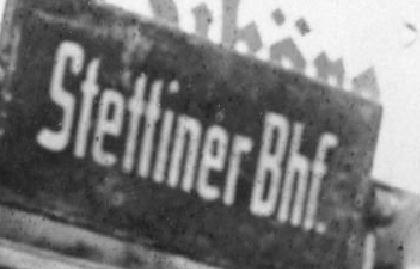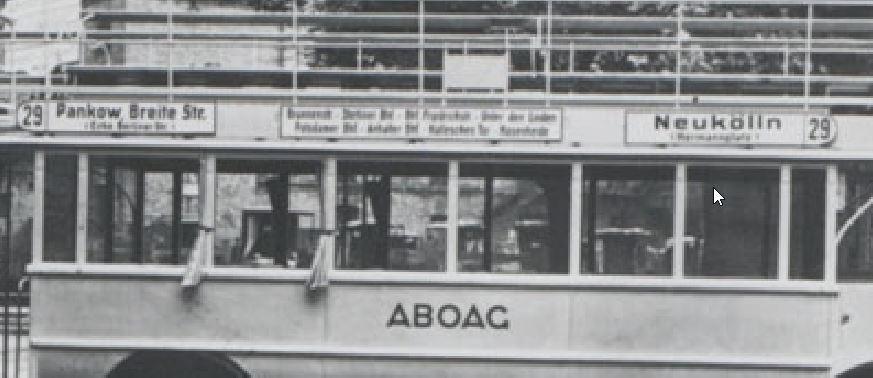
Suche Schrift an Fahrzeugen der ABOAG/BVG (Berliner Verkehr) aus der Vorkriegszeit.
die Berliner Verkehrsbetriebe (bis 1929 ABOAG, danach BVG), verwendeten für ihre Streckenanzeige an ihren Fahrzeugen ein Schriftbild, welches ich bisher noch nicht ermitteln konnte.
Anbei sind einige Abbildungen von Streckenschildern (Netzfunde/Buchkopien). Vielleicht könnt ihr mir dazu weiterhelfen.
Ich vermute, dass es eine Schrift ist, die ähnlich bei der Länder- oder Reichsbahn, speziell für das Unternehmen erstellt wurde und darüber hinaus nicht weiter im Gebrauch war.
Es würde mir auch helfen, eine sehr ähnliche Schrift zu finden. Die der Schrift vorkommenden (aus meiner Sicht) Besonderheiten wie die Gestaltung des große "S" oder kleinen "g" würde ich dann anpassen. Anpassen für Schilder, die ich im Modellbau verwenden will.
Solche Schilder waren entweder von Schildermalern handgemalt oder es gab einen nur intern verwendeten Buchstabensatz, der keinen Namen brauchte, weil er nicht gehandelt wurde. Man wird das also mit großer Wahrscheinlichkeit nicht benennen können.
Ausnahme: Neukölln und Wilmersdorf könnten auf der DIN 1451 beruhen.
Wobei der, zumindest firmenintern, standardisiert war. Denn alle Fahrzeuge, Busse und Straßenbahnen, hatten über Jahrzehnte diese Schrift im Einsatz.
Ich werde mir mal Plakative Grotesk, Schilder Grotesk und Sturkopf Grotesk näher anschauen und Buchstaben entsprechend ändern. Beispiel das kleine "a", welches ja so eine Art Hängebauch hat.
Hatte schon Kontakt aufgenommen. War auch im BVG Archiv und habe diverse digitale Bibliotheken geflöht. Hat alles keinen Erfolg gebracht.
Das liegt wahrscheinlich daran, dass das BVG Archiv 1943 durch einen Bombenangriff fast komplett zerstört wurde. Es liegen somit zur Geschichte des Berliner Nahverkehrs aus der Zeit vor dem Krieg so gut wie gar keine Unterlagen vor.
Der Tip mit der "Berliner Wand" ist gut. Habe schon einige Wiegel-Fonts. Der ist mir scheinbar durch die Lappen gegangen. Übrigens scheint Peter Wiegel nicht mehr aktiv zu sein. Webseite off.
Ich werde aus einer Kombination verschiedener Fonts (Skalierung, Linienstärke usw.) schon in die Richtige Richtung gehen.